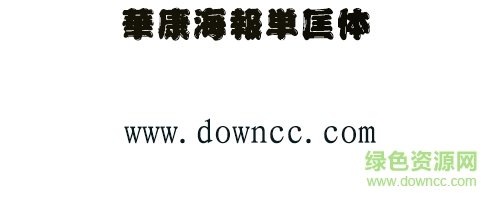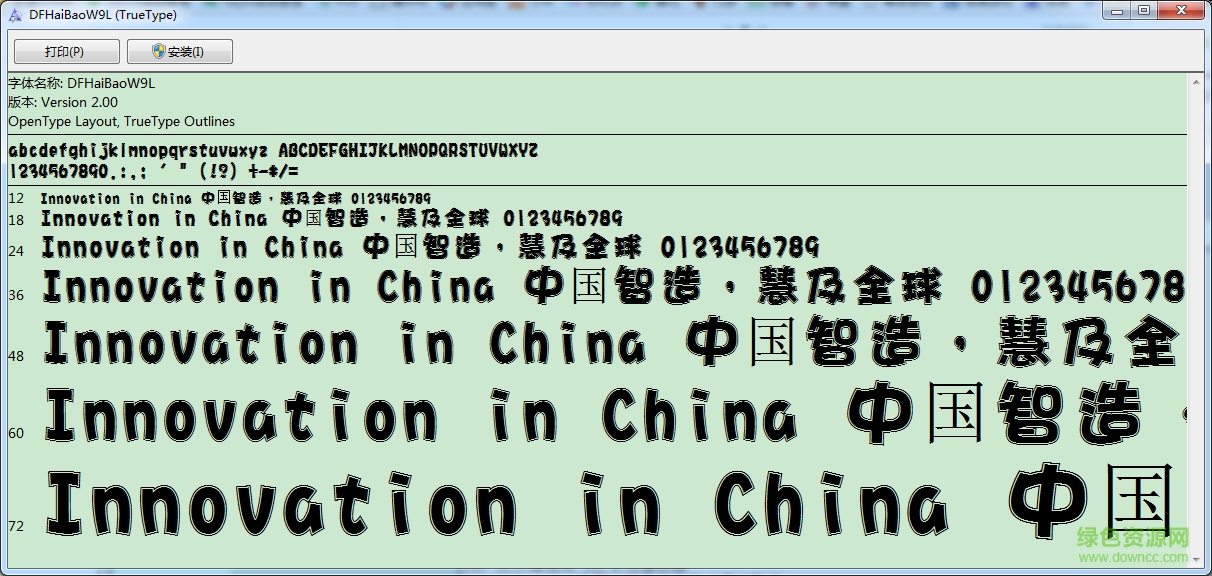
華康海報(bào)單框體w9是一款非常有特色的藝術(shù)字體,這款字體字形優(yōu)美,非常適用于廣告設(shè)計(jì)、美工制作、海報(bào)設(shè)計(jì)等各種設(shè)計(jì)領(lǐng)域,有需要的朋友歡迎來綠色資源網(wǎng)下載使用!
自華康字庫的特色字體玩呢家。該字體設(shè)計(jì)充滿藝術(shù)感,字形美觀,很適合使用于廣告設(shè)計(jì)、美工設(shè)計(jì)或標(biāo)題使用,視覺效果突出,非常優(yōu)秀!